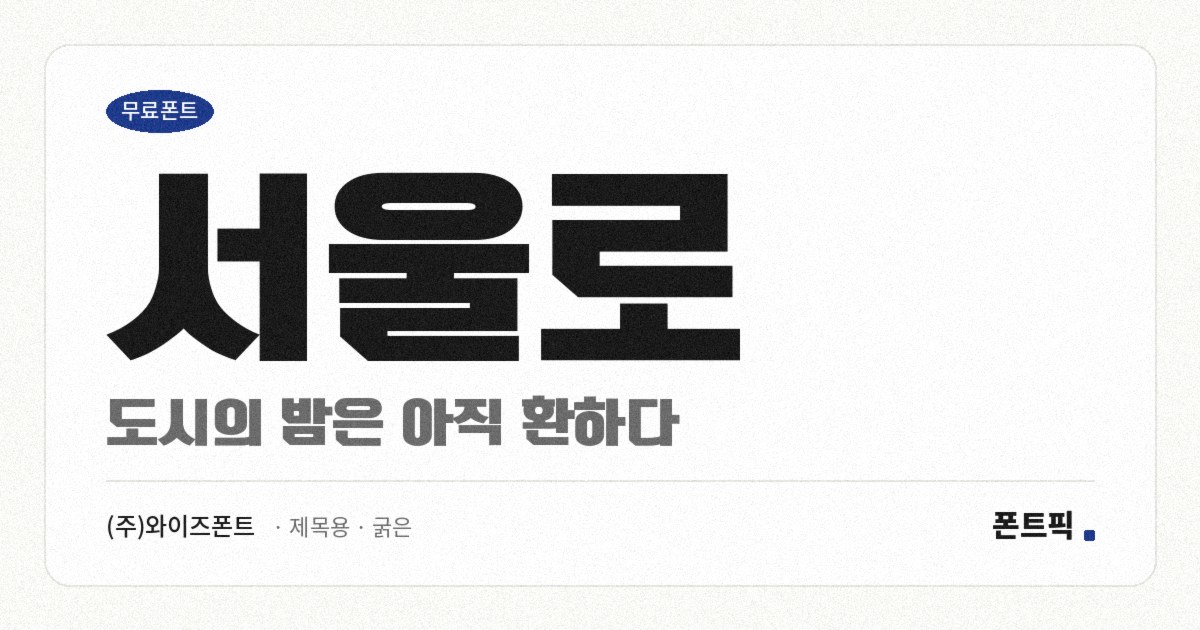
서울로
TDTDSeoulRo
- 분류제목용 · 굵은
TDTDSeoulRo
와이즈폰트의 서체 가운데 가장 굵고 진합니다. 파일에서 재어 보면 자면을 채우는 비율이 0.60으로, 폰트픽에 올라온 같은 굵기의 한글 서체 138종 가운데 두 번째로 진합니다.
형태는 손글씨가 아니라 제목용 고딕에 가깝습니다. 받침이 붙어도 높이가 거의 변하지 않는 네모틀이고 낱자는 가로로 퍼져 있으며, 세로획이 가로획보다 5할쯤 굵어 획에 강약이 있습니다. 굵은 획에 이 대비가 더해져 존재감이 큽니다.
그만큼 자리를 가립니다. 배너나 썸네일의 제목처럼 크고 짧게 쓰면 힘을 내고, 긴 문장에 깔면 획이 서로 붙어 답답해집니다. 현대 한글 11,172자를 모두 담았고 굵기는 하나입니다.